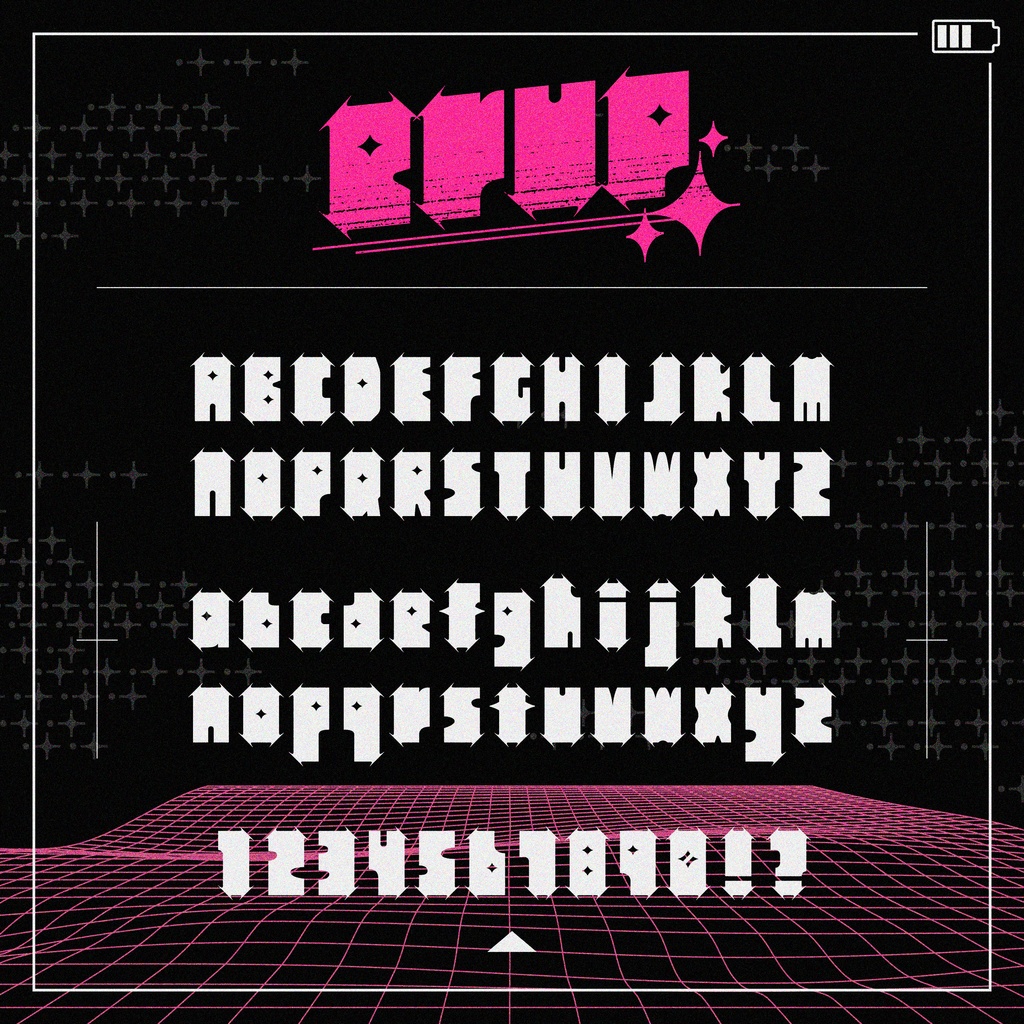
【フリーフォント】ERUP-type
【このフォントについて】 カワイイ・ポップ感のある字体をベースにしつつ、トゲトゲしいディティールをもつフォントです。 文字ひとつひとつが独特な見た目をしているので、文章を組むというよりも、タイトルやロゴなどにワンポイントで使用することをオススメします。 無償利用・商用利用問わず、自由にご使用いただけます。 印刷物のみならず、ゲームやWebなど何にでもご活用ください。 当フォントを利用した制作物などを、X(旧Twitter)で報告していただけると、とても励みになります。 不具合の修正や新しいグリフの追加が行われていますので、最新のバージョンをご確認ください。 【すずみばと書林】 《もじピジョン》と《Suzumi Designs》による2人組のフォント制作ユニットです。 共同制作のフォントを配布・販売しています。 「書林」は本来「多くの書籍が集まるところ」という意味ですが、ここでは「多くの書体が集まるところ」という意味を込めて名付けました。 新作フォントの公開やバージョンの更新情報はそれぞれのTwitterでアナウンスしています。当フォントダウンロードの折には、フォローしていただけると幸いです。 《もじピジョン/X(旧Twitter)》https://twitter.com/Moji_Pigeon 《Suzumi Designs/X(旧Twitter)》https://twitter.com/Suzumi_Designs 【収録文字】 英数字・一部約物 (最新ver.1.0) 【更新履歴】 ver.1.0 リリース 【利用規約】 ・利用条件 1)当フォントを使用したことによるいかなる損害も使用者自身が責任を負うものとします。 2)無償利用・商用利用ともにご自由にお使いいただけます。 3)クレジットの表記は不要です。 4)当フォントの二次配布は可能ですが、その際はこのtxtファイルを添付するようにしてください。なお、二次配布の際は一言いただけると幸いです。 5)当フォントを加工・変形してご利用いただけます。 6)ゲームやWebサイトに埋め込んでご利用いただけます。 ・禁止事項 1)当フォントを公序良俗に反する目的で使用することはできません。 2)当フォントを利用したロゴマーク等の商標登録はできません。 3)当フォントデータ・プログラムを、無断で改変したものを配布することはできません。 4)当フォントの制作者を騙った発言等はできません。